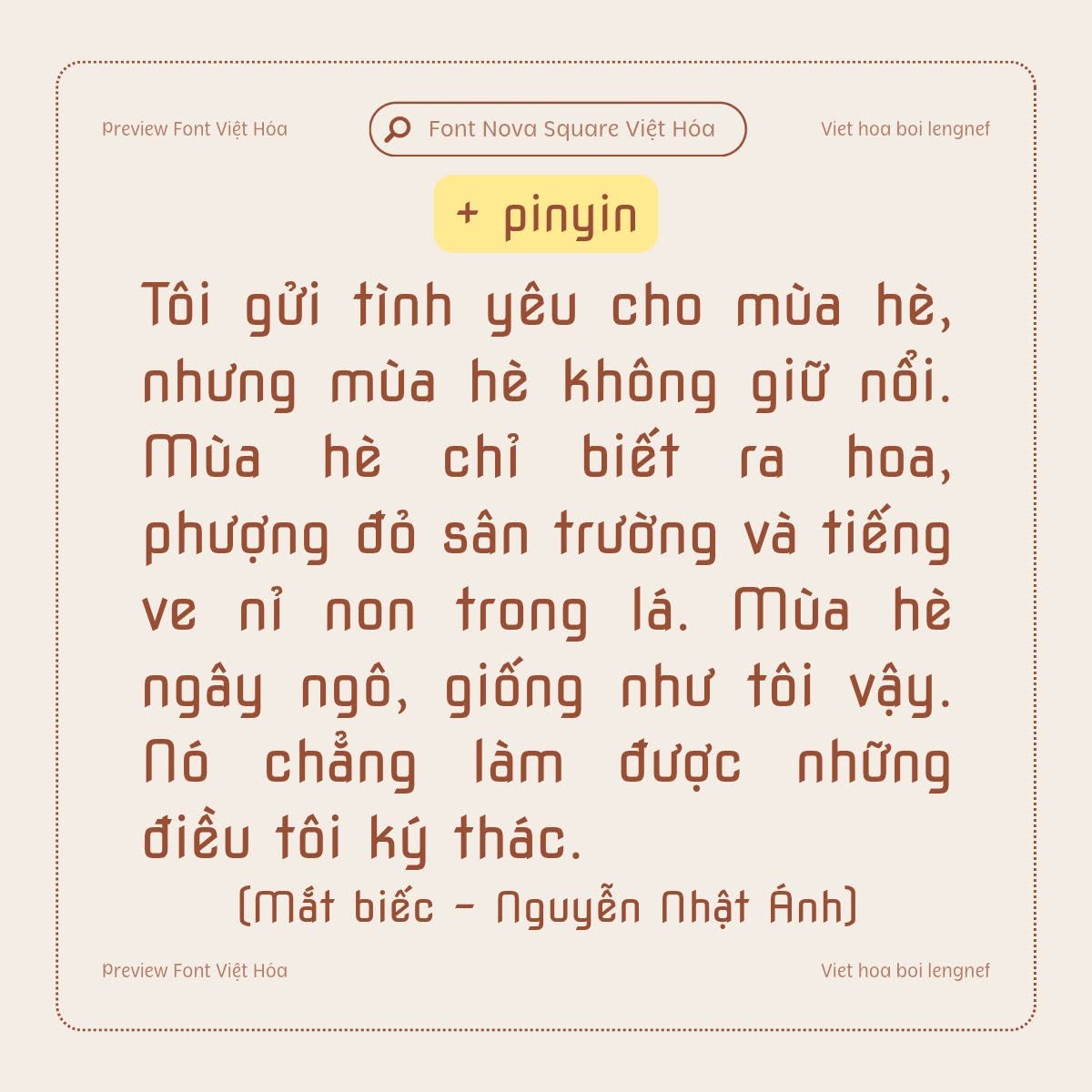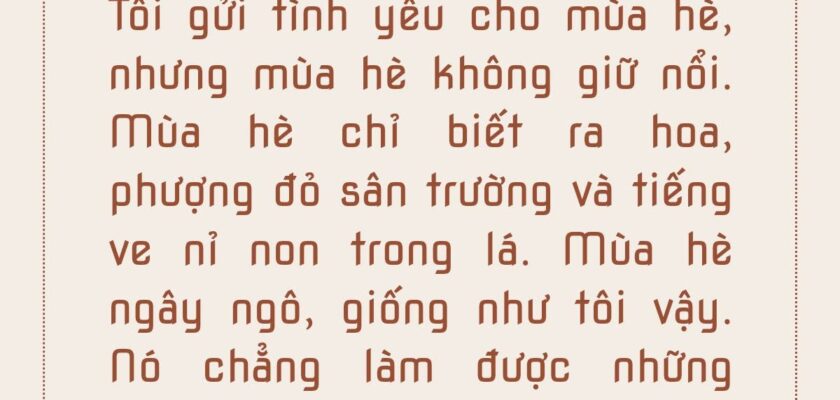
Việt hóa theo yêu cầu 23 || LF Nova Square
- Tác giả: Wojciech Kalinowski
- Việt hóa: lengnef
Nova Square là kiểu font san-serif, là kiểu chữ thường được khắc trên đá, tạo nên sự mạnh mẽ nhưng cũng ko kém phần mềm mại nhờ đường uốn cong của từng ký tự. Font này có thêm pinyin.